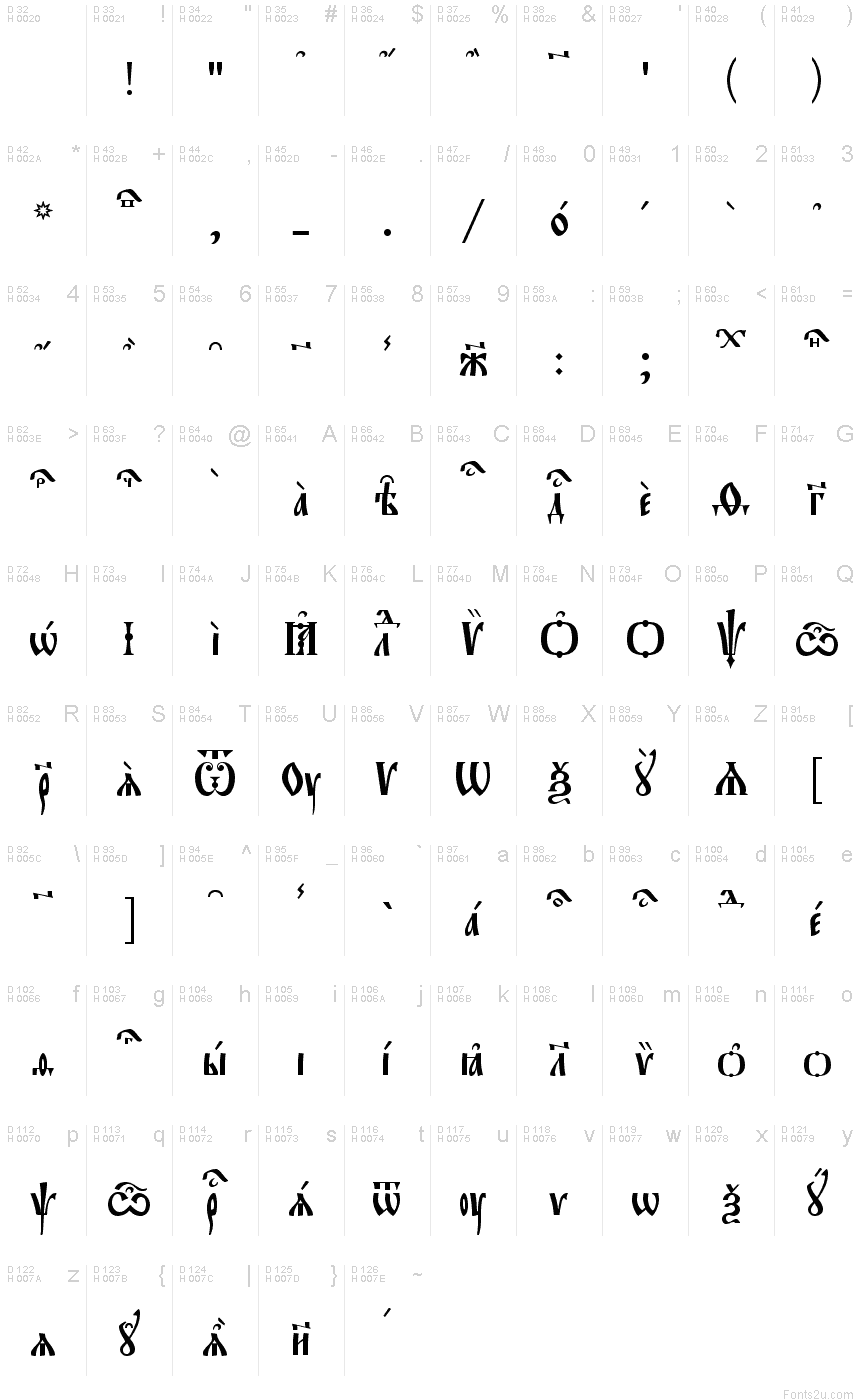
Orthodox, creata da SoftUnion Ltd e N. Andrushchenko, è un carattere display cirillico gratuito dal tono solenne e liturgico, ispirato alle lettere sacre. Le lettere mescolano forme arrotondate ampie con tratti affilati, accenti alti e dettagli a forma di croce, conferendo al carattere un aspetto da icona o manoscritto calligrafico, ben lontano da una tipografia neutra.
Si presta naturalmente a copertine di libri, grafica per mostre, titoli di poster, branding per eventi culturali e packaging a tema slavo o religioso. Essendo un font gratuito, è ideale anche per brevi titoli, cartelli, iniziali e loghi a monogramma, dove gli accenti cerimoniali e le forme allungate possono reggere l'intera composizione.